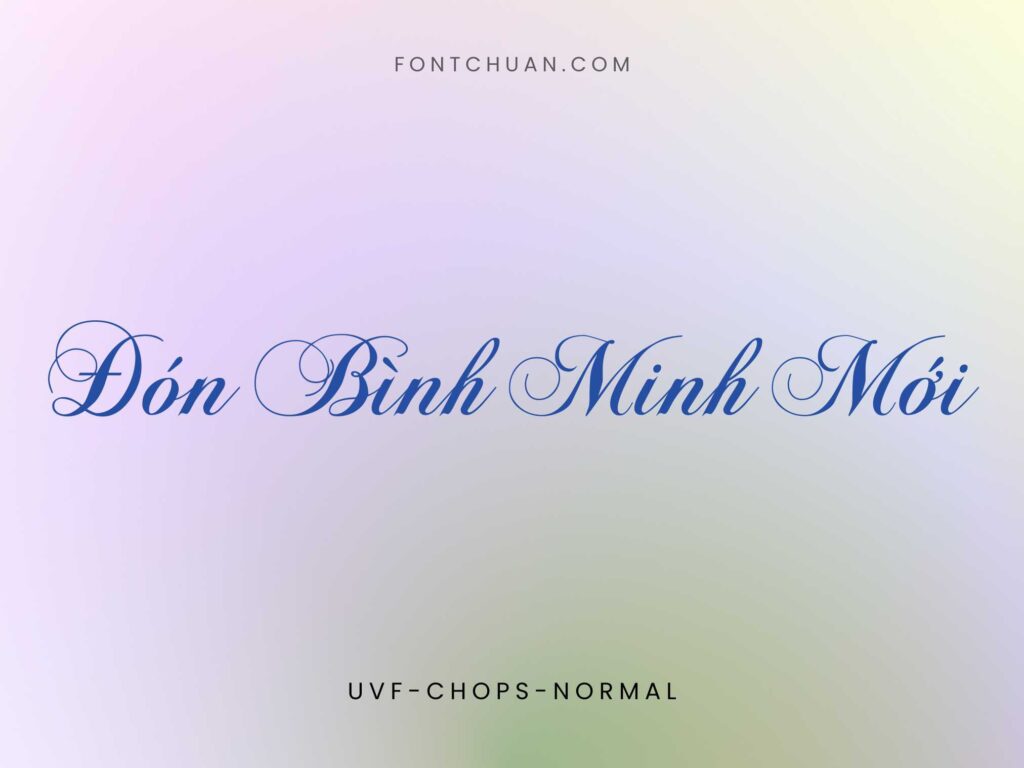
Font UVF Chops Normal Việt Hóa
UVF Chops Normal là một phông chữ script độc đáo, mang phong cách hiện đại với các đường nét mềm mại và uyển chuyển. Phông chữ này tạo cảm giác thân thiện và sáng tạo, phù hợp cho các thiết kế như tiêu đề, logo, bao bì sản phẩm và các ấn phẩm truyền thông khác. Font này được sưu tầm và đăng bởi thành viên của Font Chuẩn.
Sự phối hợp giữa đường nét mềm mại, uyển chuyển của UVF Chops Normal đã được ứng dụng để làm font sinh nhật giúp các thiết kế vừa sáng tạo, vừa thu hút người xem, mang đến cảm giác gần gũi và vui vẻ.